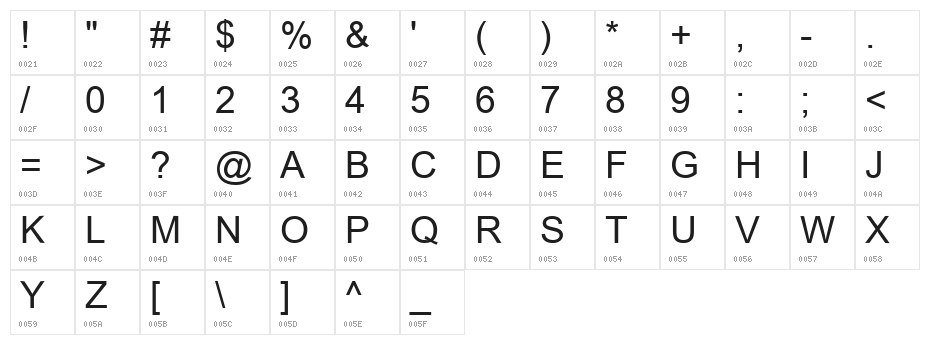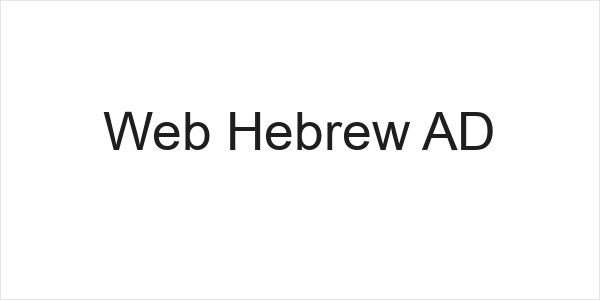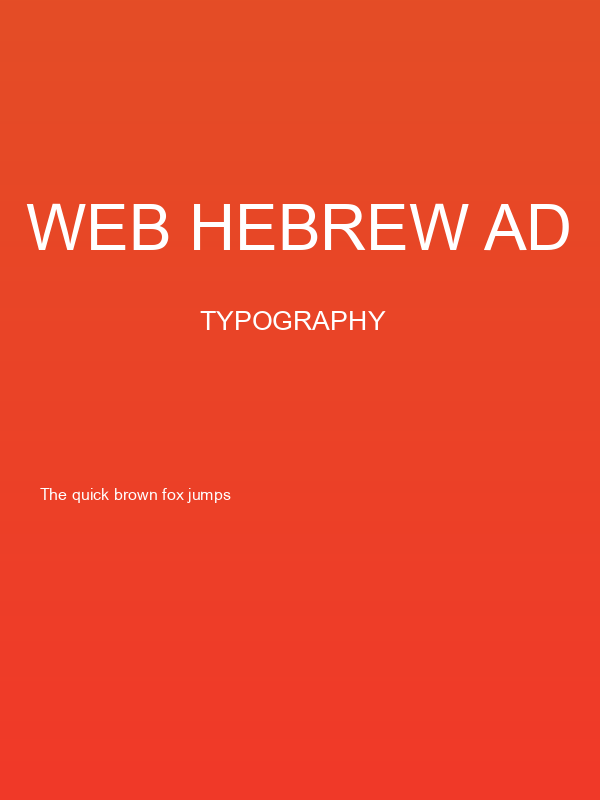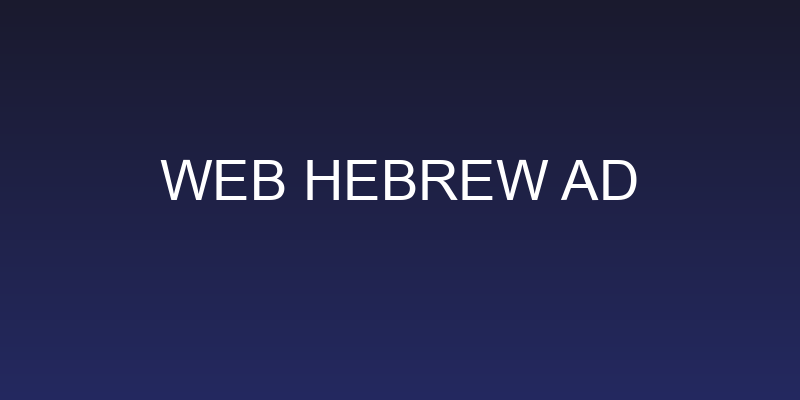
Web Hebrew AD Font
| Proiecte propuse | Ideal for web design, corporate branding, user interfaces, and print media where clarity and modern aesthetics are desired. |